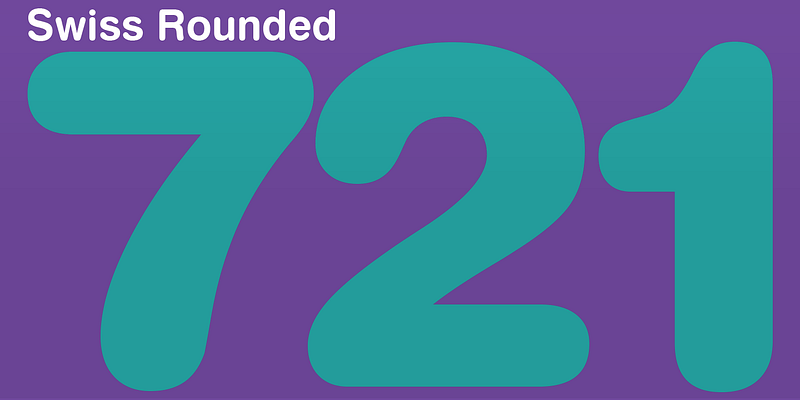
Swiss 721™ es una familia sans serif que abarca varios grosores, de fino a negro, al tiempo que incorpora algunos grosores de contorno inesperados, pero artísticamente creados e irónicamente favorecedores, para dar un toque especial a este diseño grotesco. Si combinamos estas formas de letra verticales con una versión en cursiva correspondiente, obtenemos una maravillosa herramienta, tan fácil de leer en pantalla como fuera de esta, que tiene la capacidad técnica para superar los diseños más difíciles y encajará en un sinfín de proyectos. Swiss 721 es una sans serif característica, nunca se arrepentirá de tenerla en la biblioteca. Hay quien dice que una sans serif sencilla es una de las tipografías más difíciles de diseñar. Esto se debe a que las letras se reducen a sus características más básicas, por lo que cualquier irregularidad o incoherencia en el diseño resulta visible inmediatamente. La familia tipográfica Swiss 721 es el ejemplo por antonomasia de cómo destilar las formas de las letras a su esencia, sin perder la calidez ni la energía. Swiss 721, que se basa en las tipografías sans serif de estilo años cincuenta,es una versátil familia de grosores y proporciones que encaja perfectamente en gran variedad de proyectos de diseño, ya sean impresos o interactivos, y que funciona igual de bien en encabezados de grandes carteles y en contenido de navegación en pequeñas pantallas. Swiss 721 adopta la esencia de las tipografías sans seris de los años cincuenta y los une al diseño coherente y el rango de grosores sistemático de los estilos modernos.